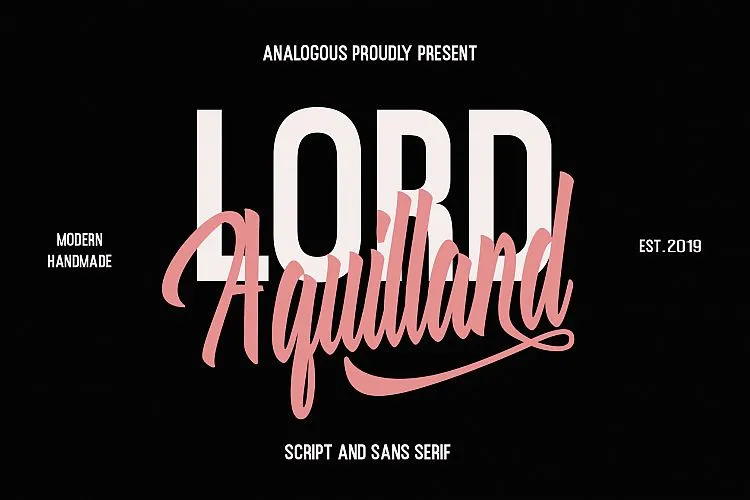
Aquilland Font Duo – Download Grátis
Bem-vindos! Aquilland Font Duo é uma dupla de tipo script-serif que se combina perfeitamente com qualquer ideia que você possa ter. Introduzimos esta fonte moderna e elegante, aquilland, cujo estilo está repleto de fortes estilos e movimento circular. Você pode começar a criar letra à mão instantaneamente, permitindo-lhe explorar o poder do design com uma linguagem única. Aquilland é um conjunto moderno de tipos combinados. A fonte apresenta três famílias, incluindo maiúsculas e minúsculas, set estilístico, ligaturas, alternativas, suporte para várias línguas, entre outros recursos úteis que permitem a você misturar e combinar seu design. Aquilland é perfeito para qualquer aplicação gráfica, como design de logomarca, etiquetas, selos, designs para roupas, e muito mais.